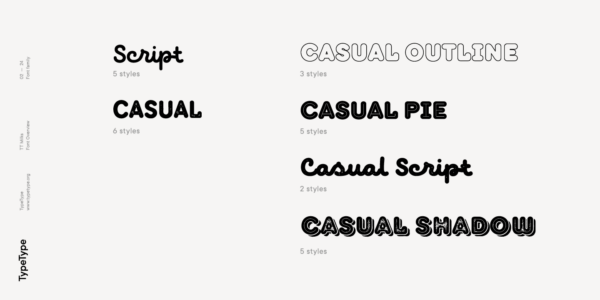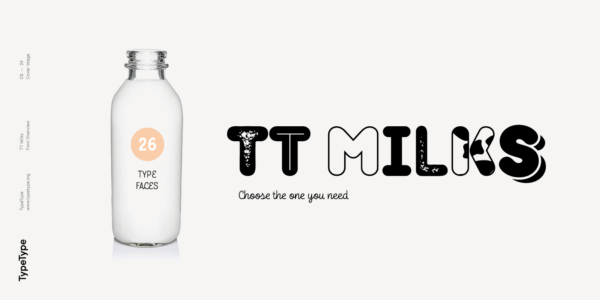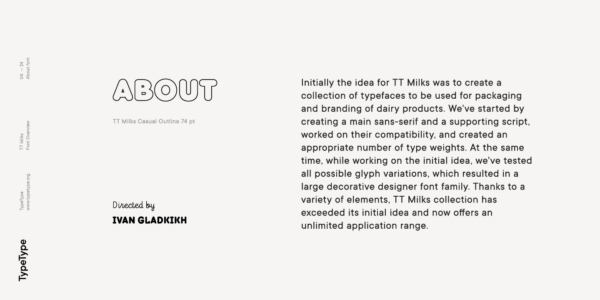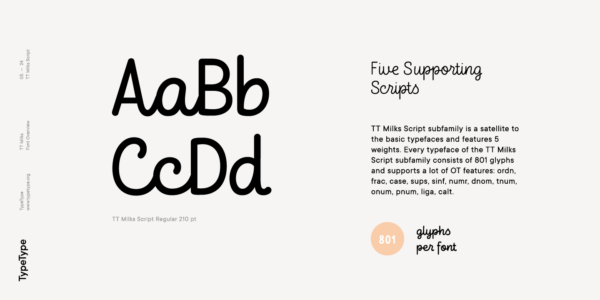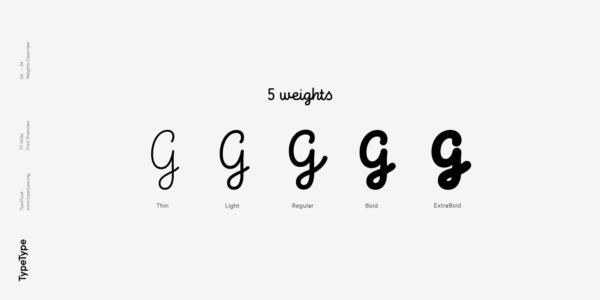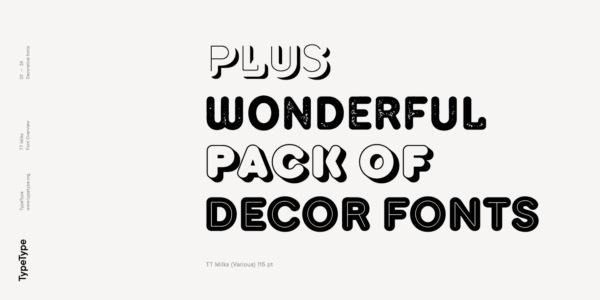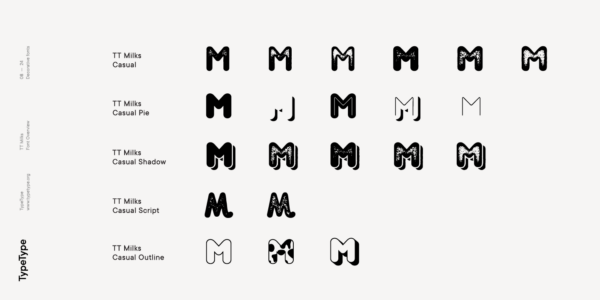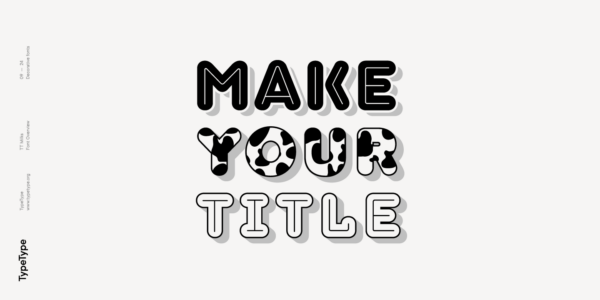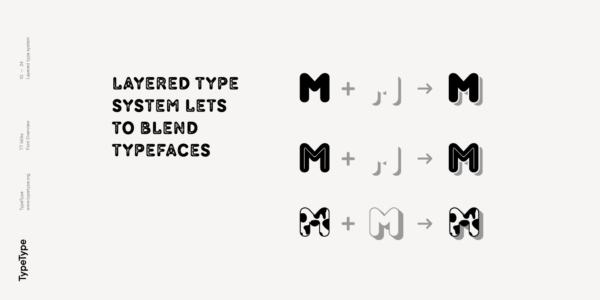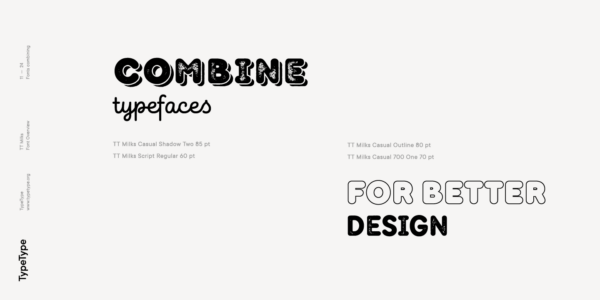
TT Milks
TT Milks — ТТ Милкс
Произносится «ТТ Милкс». «Milks» — производное слово от milk, в переводе с английского «молоко». Буквы «TT» являются аббревиатурой названия компании.
TT Milks — дизайнерская гарнитура с мягким, нежным и милым характером. Включает декоративные и рукописные начертания.
Коллекция шрифтов для использования в упаковке и брендинге
В процессе работы над идеей мы тестировали графические вариации глифов, что в конце концов привело к появлению большого декоративного семейства. Благодаря разнообразным элементам коллекция вышла за границы первоначальной задумки и предлагает неограниченные варианты применения. Коллекция Milks включает несколько подсемейств: TT Milks Script, TT Milks Casual Script, TT Milks Casual, TT Milks Casual Shadow, TT Milks Casual Pie, TT Milks Outline.
Все начертания, относящиеся к подсемействам TT Milks Casual и TT Milks Outline, содержат только прописные знаки
TT Milks Casual Shadow — версия с большей разрядкой, а также с эффектом тени
Коллекция шрифтов для брендинга упаковки
О гарнитуре TT Milks
Первоначально идея шрифтового семейства TT Milks заключалась в том, чтобы создать коллекцию шрифтов для использования в упаковке и брендинге молочной продукции. Мы начали с создания гротеска и поддерживающего его скрипта, проработали их совместимость, создали достаточное количество шрифтовых весов.
В тоже время в процессе работы над первоначальной идеей мы тестировали всевозможные графические вариации глифов, что в конце концов привело к появлению большого декоративного дизайнерского шрифтового семейства. Благодаря множеству разнообразных элементов коллекция Milks вышла за границы первоначальной задумки и теперь предлагает совершенно неограниченные варианты применения.
Шрифтовая коллекция Milks включает в себя несколько подсемейств и состоит в сумме из 26 начертаний:
Подсемейство TT Milks Script является сателлитом к основной гарнитуре и представлена в 5 весовых начертаниях. Каждое начертание подсемейства TT Milks Script состоит из 848 глифов и поддерживает большое количество OT фич: ordn, frac, case, sups, sinf, numr, dnom, tnum, onum, pnum, liga, calt;
TT Milks Casual Script — это два скриптовых начертания, с разными степенями потертости;
В Milks Casual мы собрали 6 начертаний — уникальный Black под именем 900 в трех вариациях потертостей и Bold под именем 700 также в трех вариациях потертостей;
TT Milks Casual Shadow — версия гарнитуры с большей разрядкой, а также с эффектом тени. Здесь есть чистая версия с тенью, три варианта потертостей с тенями, а также инлайн с потертостями и тенью — всего 5 начертаний;
TT Milks Casual Pie — это специальный набор начертаний, которые можно легко комбинировать между собой, с использованием разных слоев. В комплект подсемейства входят два основных начертания — черное и инлайн, а также начертание с чистой тенью и инлайн с тенью;
Завершает коллекцию TT Milks Outline, состоящий из забавных сверхакцидентных начертаний общим количеством 3 штуки — аутлайт, аутлайн с тенью и версия с паттерном шкуры коровы.
Все начертания, относящиеся к подсемействам TT Milks Casual и TT Milks Outline, содержат только прописные знаки и поддерживают табулярные цифры и чувствительность к регистру.